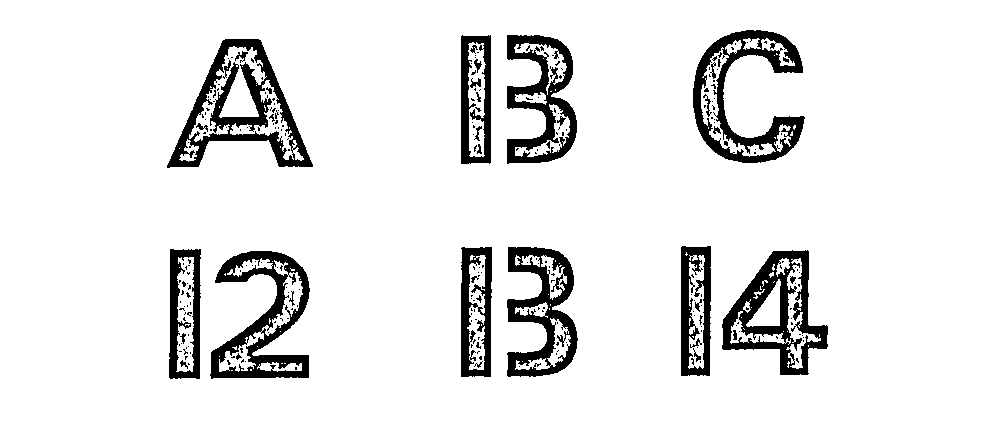
Font bei dem B und 13 gleich aussehen...
Hallo ich suche einen Font mit dem ich das Bild nachbauen kann...
A B C
12 13 14
wobei B und 13 identisch aussehen sollen.
Das könnte funktionieren, wenn ich wüßte wie ich das B zerschneiden soll. Ich schreibe Texte mit Xelatex und wollte das Beispiel nicht als Bild einbinden. Ich hatte gehofft, dass jemand den Font wiedererkennt.... oder einen ähnlichen.
Habs aus einem Buch herauskopiert. Danke für den Link, ich habe schon zwei Fonts gefunden mit denen ich das Nachbauen kann. Ganz vielen Dank, damit ist mein Problem gelöst.